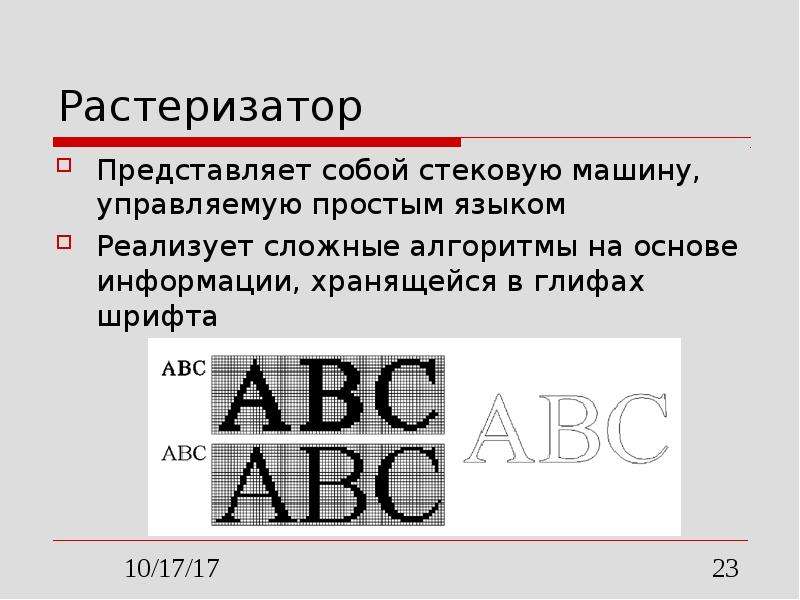
Вывод текста и шрифты Отвагин Алексей Владимирович, доцент каф. ЭВМ, к.т.н., а. 505-5
Содержание Понятие шрифта, характеристики шрифта Виды шрифтов Вывод текста в графическом интерфейсе
Основные понятия
Кодировки Содержат 256 символов (первые 128 стандартные) Вторая половина содержит символы национальных алфавитов, денежных знаков, дополнительные...
Кодировки Содержат 256 символов (первые 128 стандартные) Вторая половина содержит символы национальных алфавитов, денежных знаков, дополнительные символы и т.д. Идентификатор кодировки от 0 до 255
Unicode Новый стандарт кодировок (16 разрядное представление) Позволяет представить большинство символов различных языков мира Группируется на...
Unicode Новый стандарт кодировок (16 разрядное представление) Позволяет представить большинство символов различных языков мира Группируется на логические зоны для представления отдельных классов символов
Глиф Кодировка определяет лишь логическую группировку и представление символов Графическая форма символа называется глифом
Свойства глифов Обычно существует однозначное соответствие между кодом символа и глифом Глифы могут определяться контекстом использования символа...
Свойства глифов Обычно существует однозначное соответствие между кодом символа и глифом Глифы могут определяться контекстом использования символа Глиф может быть составным Глиф может являться комбинацией символов - лигатурой
Примеры сложных глифов
Элементы глифов Базовая линия Ножка Засечка Внутрибуквенный просвет Надстрочный элемент Полуовал Ушко Х-высота Подстрочный элемент Петля Связь...
Элементы глифов Базовая линия Ножка Засечка Внутрибуквенный просвет Надстрочный элемент Полуовал Ушко Х-высота Подстрочный элемент Петля Связь Каплевидный элемент
Определение шрифта Шрифт – совокупность глифов, обладающих сходным графическим стилем, для которой определено отображение кодировки в глифы Шрифт...
Определение шрифта Шрифт – совокупность глифов, обладающих сходным графическим стилем, для которой определено отображение кодировки в глифы Шрифт может поддерживать несколько кодировок Глифы являются базовым компонентом шрифта
Имя шрифта – символьная строка, определяющая его семейство и начертание Семейство – группа шрифтов, обладающая сходным начертанием и одним...
Имя шрифта – символьная строка, определяющая его семейство и начертание Семейство – группа шрифтов, обладающая сходным начертанием и одним названием Начертание – видоизменение шрифта в семействе (нормальное, полужирное, наклонное, подчеркнутое и т.д.)
Разновидности шрифтов Моноширинный – все символы имеют одинаковую ширину (консольные шрифты) Пропорциональный – глифы имеют разную ширину Roman –...
Описание слайда:
Разновидности шрифтов Моноширинный – все символы имеют одинаковую ширину (консольные шрифты) Пропорциональный – глифы имеют разную ширину Roman – переменная толщина линий и засечки Swiss – переменная толщина без засечек Modern – постоянная толщина линий без засечек Script – имитация рукописного текста Decorative – без ограничений
Слайд 13
Примеры семейств шрифтов
Описание слайда:
Примеры семейств шрифтов
Слайд 14
Методы представления шрифта Растровые шрифты Векторные шрифты Шрифты TrueType
Описание слайда:
Методы представления шрифта Растровые шрифты Векторные шрифты Шрифты TrueType
Слайд 15
Растровые шрифты Пикселы, образующие глиф, являются растровым изображением Для разных разрешений экрана требуются разные наборы шрифтов Шрифты плохо...
Описание слайда:
Растровые шрифты Пикселы, образующие глиф, являются растровым изображением Для разных разрешений экрана требуются разные наборы шрифтов Шрифты плохо масштабируются к произвольному размеру
Слайд 16
Заголовок шрифта typedef struct { WORD Version; // 0x200 для 2.0, 0x300 для 3.00 DWORD Size; // Размер файла шрифта CHAR Copyright[60]; WORD Type; //...
Описание слайда:
Заголовок шрифта typedef struct { WORD Version; // 0x200 для 2.0, 0x300 для 3.00 DWORD Size; // Размер файла шрифта CHAR Copyright[60]; WORD Type; // Растровый, если Type & 1 == 0 WORD Points; // Номинальный размер в пойнтах (1/72 дюйма) WORD VertRes; // Вертикальное разрешение WORD HorizRes; // Горизонтальное разрешение WORD Ascent; WORD Descent; WORD IntLeading; WORD ExtLeading; BYTE Italic; BYTE Underline; BYTE StrikeOut; WORD Weight; BYTE CharSet; WORD PixWidth; // 0 для пропорционального WORD PixHeight; BYTE Family; // Семейство WORD AvgWidth; // Ширина символа 'x‘ WORD MaxWidth; // Максимальная ширина BYTE FirstChar; // Первый символ BYTE LastChar; // Последний символ BYTE DefaultChar; // Заполнитель BYTE BreakChar; // Пробел } FontHeader20;
Слайд 17
Параметры шрифта
Описание слайда:
Параметры шрифта
Слайд 18
Векторные шрифты Глиф описывается последовательностью линейных отрезков Различие шрифтов в представлении данных глифа Для представления используется...
Описание слайда:
Векторные шрифты Глиф описывается последовательностью линейных отрезков Различие шрифтов в представлении данных глифа Для представления используется специальная грамматика Шрифты неплохо масштабируются
Слайд 19
Грамматика векторных шрифтов ::= { } ::= { } ::= 0x80 ::=
Описание слайда:
Грамматика векторных шрифтов ::= { } ::= { } ::= 0x80 ::=
Слайд 20
Шрифты TrueType Разработаны компанией Apple Контуры глифа представляются прямыми линиями и кривыми При масштабировании кривые остаются плавными...
Описание слайда:
Шрифты TrueType Разработаны компанией Apple Контуры глифа представляются прямыми линиями и кривыми При масштабировании кривые остаются плавными Векторные шрифты определяют линии, а TrueType – контуры глифа
Слайд 21
Отображение шрифта Загружается контур шрифта и подается в растеризатор Контур масштабируется до нужного размера в точках для нужной разрешающей...
Описание слайда:
Отображение шрифта Загружается контур шрифта и подается в растеризатор Контур масштабируется до нужного размера в точках для нужной разрешающей способности устройства Подсказки применяются к контуру, искажая его, чтобы сформировать контур, приспособленный к сетке Преобразованный контур заполняется пикселами, создавая растровый точечный рисунок Растровый точечный рисунок кэшируется и используется далее при выводе шрифта
Слайд 22
Представление символов шрифта Контур глифа состоит из ряда связанных контуров и линий, которые определены рядом точек, описывающих квадратичные...
Описание слайда:
Представление символов шрифта Контур глифа состоит из ряда связанных контуров и линий, которые определены рядом точек, описывающих квадратичные B-сплайны Используются два типа точек, чтобы определить кривые: те, которые находятся на кривой и те, которые не находятся Прямые линии определяются их оконечными точками
Слайд 23
Растеризатор Представляет собой стековую машину, управляемую простым языком Реализует сложные алгоритмы на основе информации, хранящейся в глифах...
Описание слайда:
Растеризатор Представляет собой стековую машину, управляемую простым языком Реализует сложные алгоритмы на основе информации, хранящейся в глифах шрифта
Слайд 24
Растеризация шрифта TrueType Выполняется подгонкой глифа с помощью специальных команд Обеспечивает: Одинаковую толщину линий Сохранение размеров...
Описание слайда:
Растеризация шрифта TrueType Выполняется подгонкой глифа с помощью специальных команд Обеспечивает: Одинаковую толщину линий Сохранение размеров внутри одного глифа и между глифами Сохранение симметрии и других элементов глифа (например, засечек)
Слайд 25
Подгонка при растеризации
Описание слайда:
Подгонка при растеризации
Слайд 26
Логические шрифты Используются для вывода в графическом интерфейсе Обеспечивают независимость от устройства Поддерживают использование кодировок...
Описание слайда:
Логические шрифты Используются для вывода в графическом интерфейсе Обеспечивают независимость от устройства Поддерживают использование кодировок Позволяют создавать шрифты заданного размера Реализуют некоторые начертания (подчеркивание и перечеркивание)
Слайд 27
Структура описания шрифта sealed class Font : MarshalByRefObject, ICloneable, ISerializable, IDisposable { public Font(...); // Свойства public bool...
Описание слайда:
Структура описания шрифта sealed class Font : MarshalByRefObject, ICloneable, ISerializable, IDisposable { public Font(...); // Свойства public bool Bold { get; } public FontFamily { get; } public byte GdiCharSet { get; } public bool GdiVerticalFont { get; } public int Height { get; } public bool Italic { get; } public string Name { get; } public float SizeInPoints { get; } public bool Strikeout { get; } public FontStyle Style { get; } public bool Underline { get; } public GraphicsUnit Unit { get; } }
Слайд 28
Структура описания семейства шрифтов sealed class FontFamily : MarshalByRefObject, IDisposable { public FontFamily(string name); // Свойства public...
Описание слайда:
Структура описания семейства шрифтов sealed class FontFamily : MarshalByRefObject, IDisposable { public FontFamily(string name); // Свойства public static FontFamily[] Families { get; } public static FontFamily GenericMonospace { get; } public static FontFamily GenericSansSerif { get; } public static FontFamily GenericSerif { get; } public string Name { get; } // Методы public int GetCellAscent(FontStyle style); public int GetCellDescent(FontStyle style); public int GetEmHeight(FontStyle style); public static FontFamily[] GetFamilies(Graphics graphics); public int GetLineSpacing(FontStyle style); public string GetName(int language); public bool IsStyleAvailable(FontStyle style); }
Слайд 29
Создание шрифта FontFamily family = new FontFamily("Arial"); Font font = new Font(family, 12, FontStyle.Bold | FontStyle.Italic); После...
Описание слайда:
Создание шрифта FontFamily family = new FontFamily("Arial"); Font font = new Font(family, 12, FontStyle.Bold | FontStyle.Italic); После создания шрифта GDI подбирает соответствующий ему физический шрифт
Слайд 30
Функция вывода текста Выводит строку using( Font font = new Font("Arial", 12) ) { // Обрезает строку по символу // перевода строки...
Описание слайда:
Функция вывода текста Выводит строку using( Font font = new Font("Arial", 12) ) { // Обрезает строку по символу // перевода строки g.DrawString("line 1\nline 2", font, Brushes.Black, 10, 10); } Выводит строку, обрезая ее в границах прямоугольника g.DrawString("a long string...", font, Brushes.Black, this.ClientRectangle);
Слайд 31
Форматирование текста enum StringFormatFlags { 0, // По умолчанию DirectionRightToLeft, // Вывод справа налево DirectionVertical, // Вывод сверху...
Описание слайда:
Форматирование текста enum StringFormatFlags { 0, // По умолчанию DirectionRightToLeft, // Вывод справа налево DirectionVertical, // Вывод сверху вниз DisplayFormatControl, // Вывод управляющих символов FitBlackBox, // Помещать глифы внутрь границ LineLimit, // Вывод только полных строк MeasureTrailingSpaces, // Учитывать пробелы NoClip, // Не обрезать текст NoWrap, // Не воспринимать \n или \t }
Слайд 32
Вывод с форматированием StringFormat format = new StringFormat(); format.FormatFlags = StringFormatFlags.DirectionVertical |...
Описание слайда:
Вывод с форматированием StringFormat format = new StringFormat(); format.FormatFlags = StringFormatFlags.DirectionVertical | StringFormatFlags.NoWrap; g.DrawString("...", font, brush, rect, format);
Слайд 33
Отсечение строк enum StringTrimming { None, // без отсечения Character, // Отсечение по ближайшему символу EllipsisCharacter, // По ближайшему...
Описание слайда:
Отсечение строк enum StringTrimming { None, // без отсечения Character, // Отсечение по ближайшему символу EllipsisCharacter, // По ближайшему символу + … Word, // По ближайшему слову EllipsisWord, // По ближайшему слову + … EllipsisPath, // Отсечение с … в середине }
Слайд 34
Функции выравнивания enum StringAlignment { Center, Near, // В зависимости от направления вывода Far, // В зависимости от направления вывода }...
Описание слайда:
Функции выравнивания enum StringAlignment { Center, Near, // В зависимости от направления вывода Far, // В зависимости от направления вывода } format.Alignment = StringAlignment.Center; format.LineAlignment = StringAlignment.Center;
Слайд 35
Сглаживание шрифтов SingleBitPerPixelGridFit – Символ выводится согласно глифу, сглаживаются кривые. SingleBitPerPixel - Символ выводится согласно...
Сглаживание шрифтов SingleBitPerPixelGridFit – Символ выводится согласно глифу, сглаживаются кривые. SingleBitPerPixel - Символ выводится согласно глифу. AntiAliasGridFit- Символ выводится согласно сглаженному глифу с учетом подсказок. AntiAlias - Символ выводится согласно сглаженному глифу без учета подсказок сглаживания. ClearTypeGridFit - Символ выводится согласно глифу ClearType с учетом подсказок сглаживания.